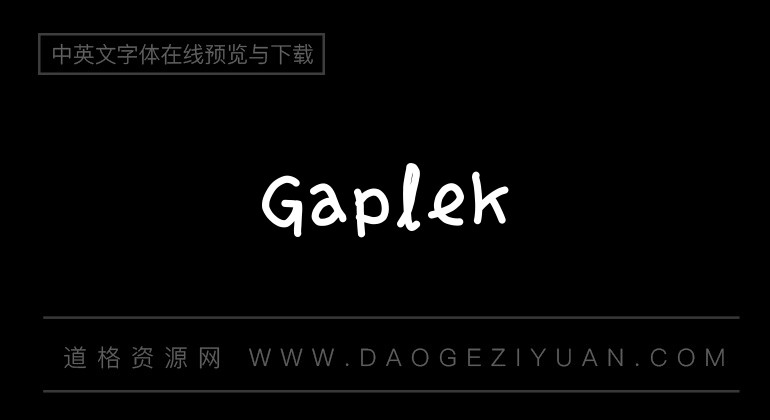
Gaplek 字体是一种具有独特个性的字体,它结合了传统的印尼文字和西方字体的元素,以节省空间,提高字体可读性。它适合用在标题、标签、广告、报纸和其他文本中,也可以用在网络和移动设备上。Gaplek 字体拥有完整的字母、数字和符号,支持多种语言,还拥有大量的细节,可以帮助您让您的设计更加出色。内容介绍
Gaplek是一款非常不错的手写艺术字体,具有很好的视觉感,适合于文化类的宣传设计、商业类品牌的广告和产品包装设计以及个性化文字排版等较多场景。